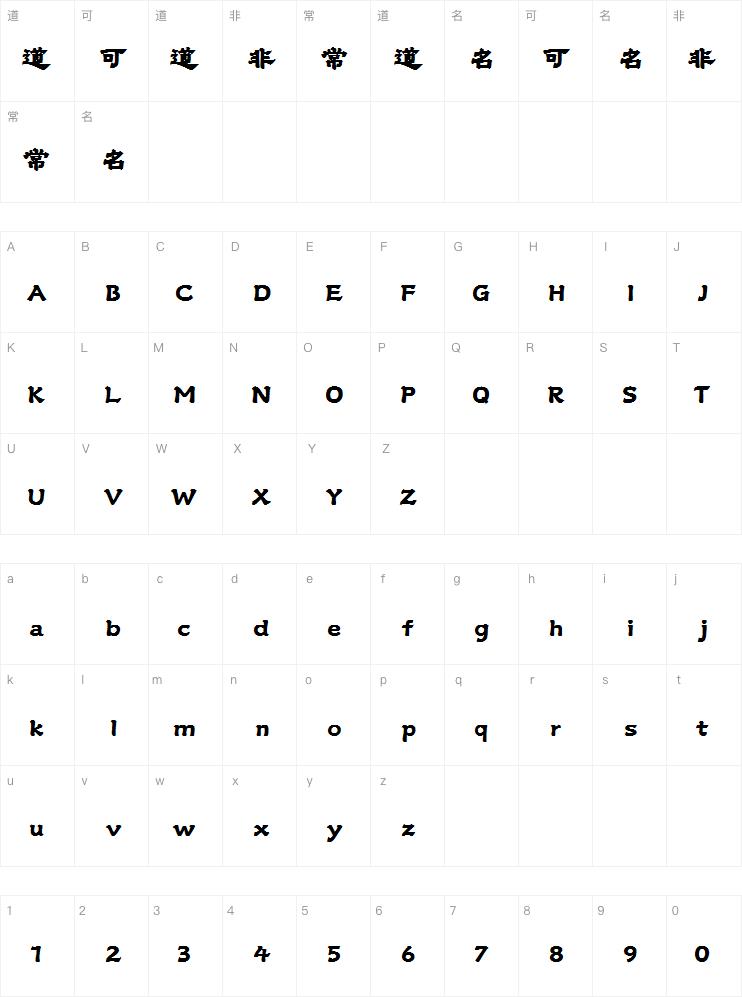
山海流年隶,是一款全新的字体,包含简繁汉字9169个,符号200+个,是一款隶书字体。该字体古朴浑厚,笔画与字形间透露着隶书的古雅和刚劲的特点,在浑厚的同时而又极富张力,桀骜不驯的特性,霸气外露。该字体汲取古人隶书书法中创新,结合当代设计视觉环境,融入现代审美。它的笔画充满力量感,组合搭配极富强烈的节奏感。在粗细的纵横间,拥有非常规的张力特性。从而使得该字体字形在浑厚的同时而又极富张力。它的笔画充满力量感的同时,又蕴含着朴拙感。在粗细的纵横间,拥有非常规的张力特性。笔画的楷书运笔笔势效果使字体的气息更加流畅,笔画间的关系密不可分,同时也增加了字体的自由洒脱之感。这款字体古韵悠扬而不失灵动,静中有动,收放有序,适合作为标题字体应用于书籍封面、影视标题、展览广告等多种场景。